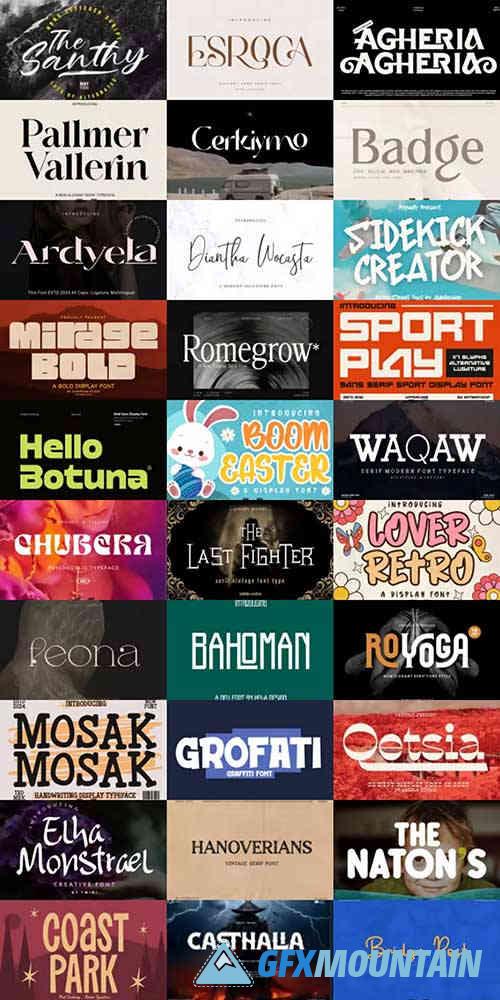
Script Font Collection Bundle – 20 Fonts
Script Font Collection Bundle – 20 Fonts: إضافة أنيقة لمشاريعك التصميمية
نظرة عامة
حزمة Script Font Collection تقدم لك 20 خطاً يدوياً مميزاً لرفع مستوى تصاميمك. هذه المجموعة المختارة بعناية مثالية للمصممين، المسوقين، وكل من يبحث عن لمسة فنية احترافية في أعماله.
مميزات الحزمة
1. تنوع في الأنماط
• خطوط كلاسيكية بأناقة يدوية
• خطوط عصرية بمظهر مرن
• خطوط ديكورية للعناوين المميزة
2. جودة عالية
• جميع الخطوط متوافقة مع OpenType
• دعم أحرف خاصة ورموز إضافية
• بدائل غليفية متعددة لكل حرف
أبرز الخطوط في المجموعة
1. Elegant Script – للتصاميم الرسمية
2. Brush Flow – لمظهر فني حر
3. Signature Style – لتقليد التوقيعات
4. Playful Hand – للتصاميم المرحة
5. Vintage Calligraphy – للذوق الكلاسيكي
حالات الاستخدام
للعلامات التجارية
• تصميم شعارات مميزة
• مواد التغليف والتعبئة
• هوية بصرية متكاملة
للأعمال الإبداعية
• دعوات الأفراح والمناسبات
• تصميم الكتب والمجلات
• مواد التسويق الرقمي
الخلاصة
هذه الحزمة توفر لك:
• تنوعاً يلبي كل احتياجاتك التصميمية
نصيحة للمصممين: يمكنك دمج هذه الخطوط مع خطوط Sans-Serif لإنشاء تباين مرئي مذهل في تصاميمك.